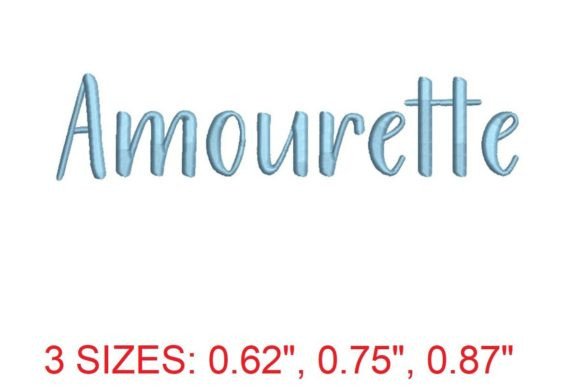
Amourette Embroidery Font
Trouver les bons éléments de conception peut être un défi, mais Amourette Embroidery Font propose une collection exceptionnelle qui rehausse instantanément votre travail.